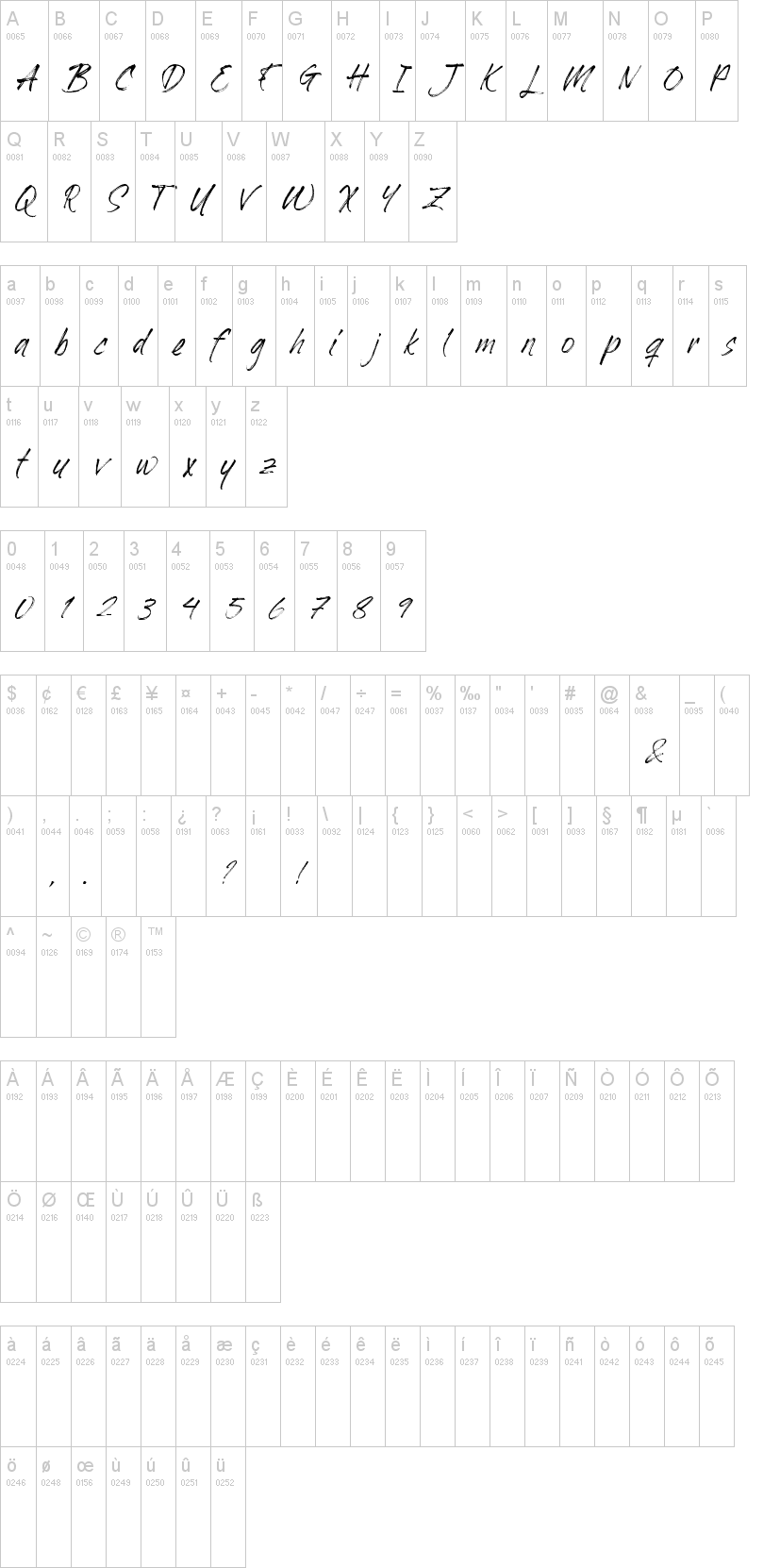
Dafiati
Dafiati 字体是一种简洁、优雅的非常特别的字体,它有着独特的外观和设计,它的设计特点是细节丰富,字体细节精细,字符间距较大,字体结构紧凑,让文字更具表现力,适合用于艺术设计、广告设计、标志设计、品牌设计等。
Dafiati是一款非常不错的手写艺术字体,具有很好的视觉感,适合于文化类的宣传设计、商业类品牌的广告和产品包装设计以及个性化文字排版等较多场景。